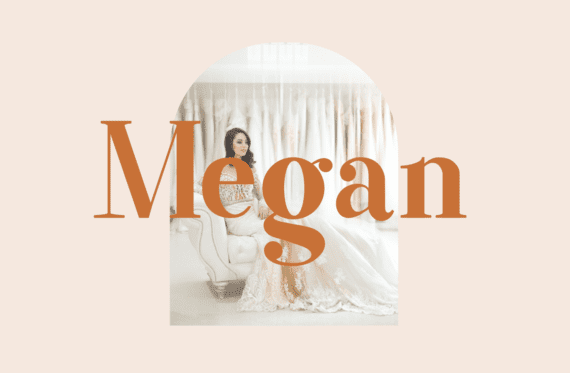
Название: Megan Font (2021)
Megan - это модный, стильный и напористый шрифт с засечками.
Мастерски разработанный, чтобы стать настоящим фаворитом, этот шрифт способен поднять каждую вашу творческую идею на самый высокий уровень!